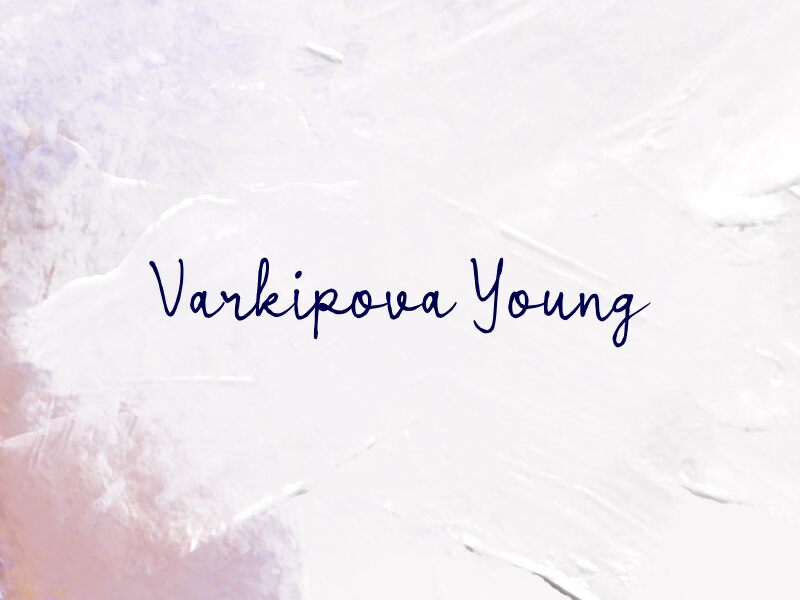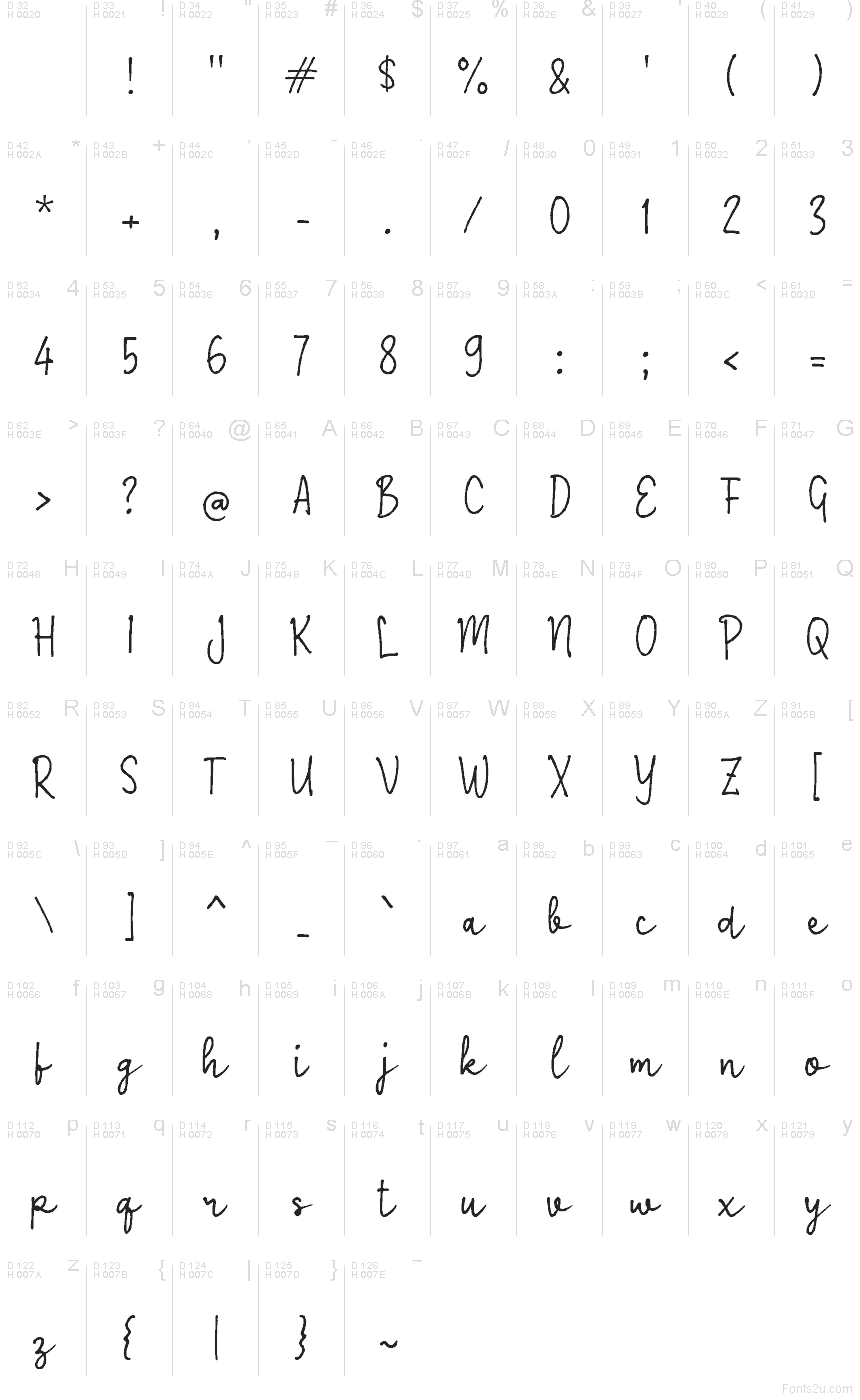
Varkipova Young
Varkipova Young от Wep — это бесплатный рукописный шрифт со свободным, юношеским ритмом и слегка «прыгающей» базовой линией. Буквы выглядят написанными на бегу, а не тщательно выверенными: высокие петли, округлые соединения и легкая небрежность придают словам по-настоящему живой и личный характер.
Он идеально впишется в дизайн в стиле блокнотных записей, меню кофеен, посты в соцсетях, подарочные бирки и легкие журнальные заголовки, где человечность важнее строгой формальности. Этот бесплатный шрифт также отлично подходит для коротких цитат, оформления карточек и упаковки — благодаря длинным выносным элементам и свободным связкам даже короткие фразы смотрятся динамично.